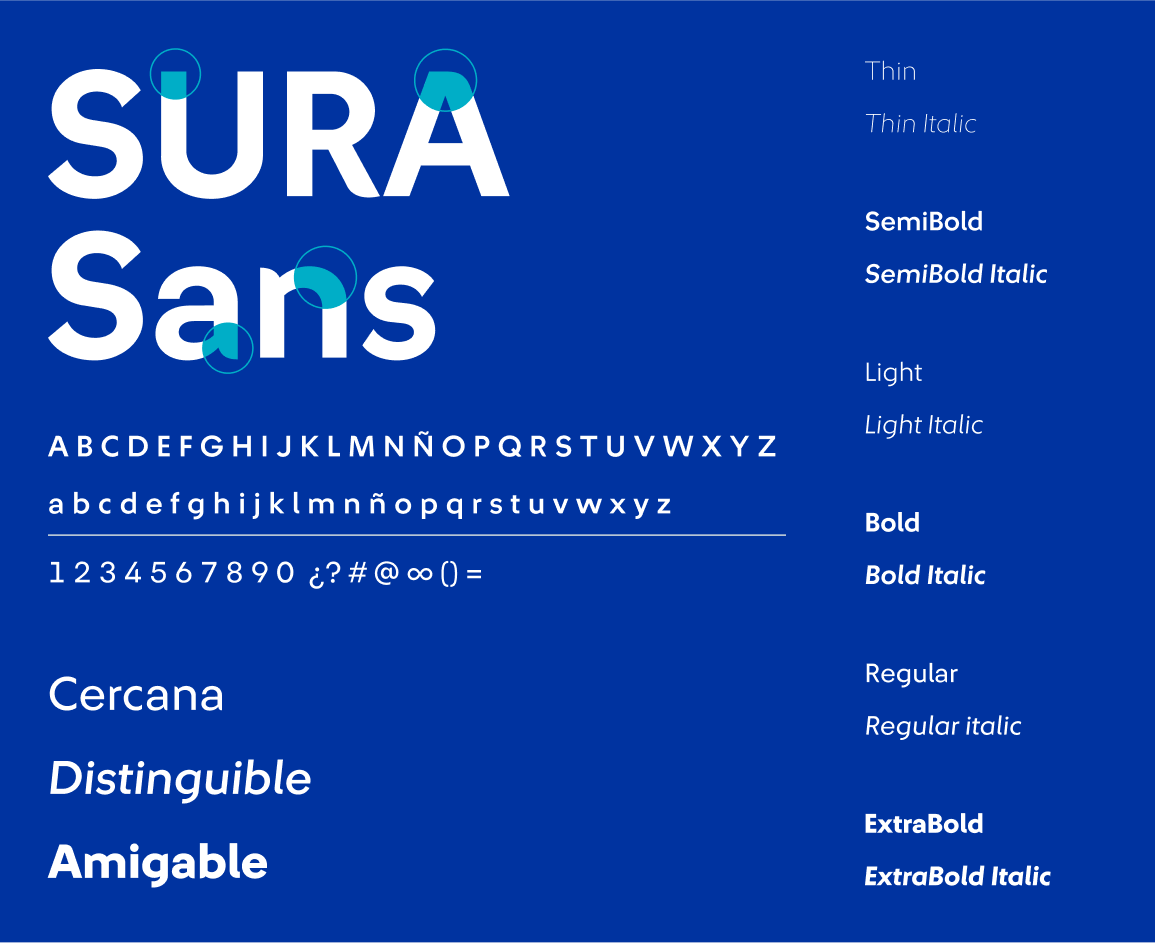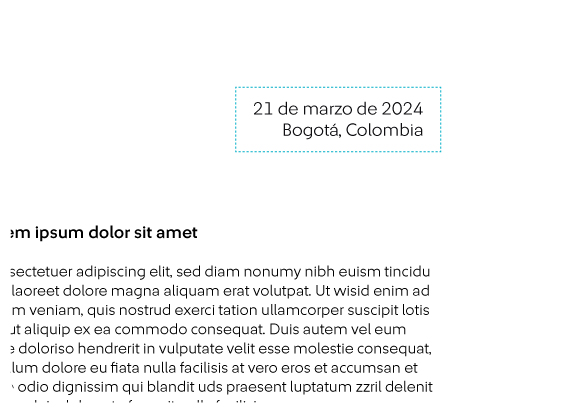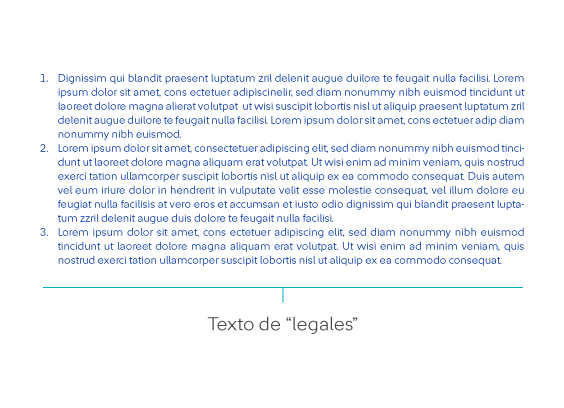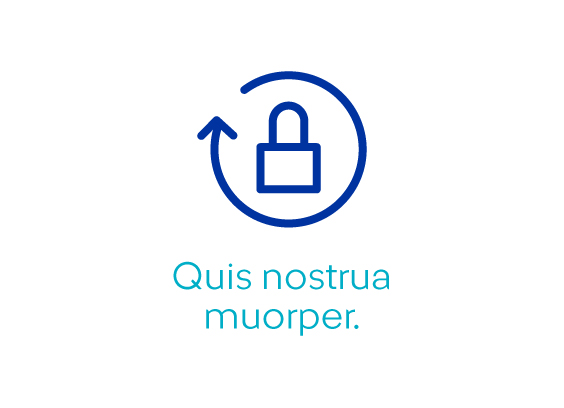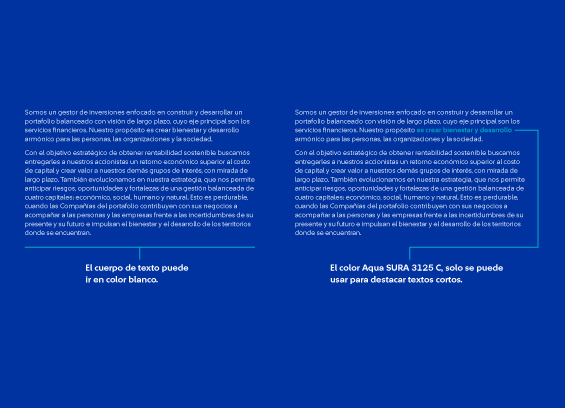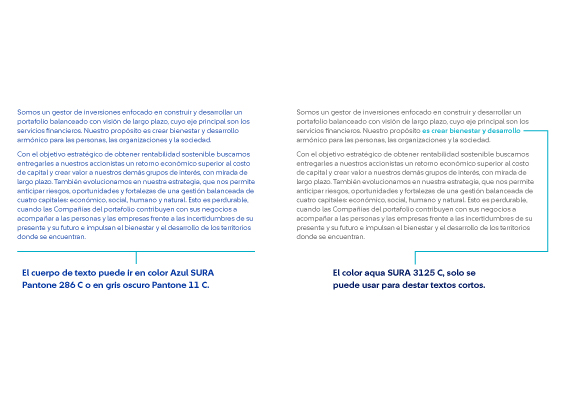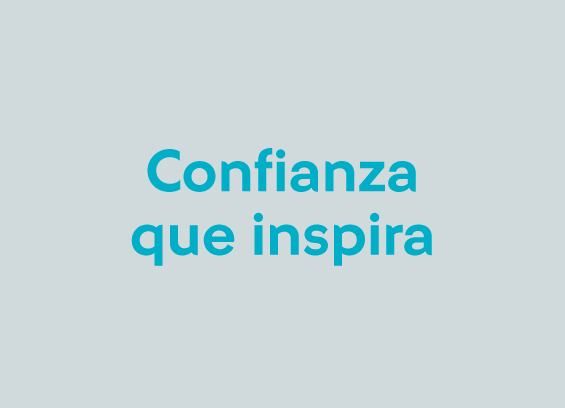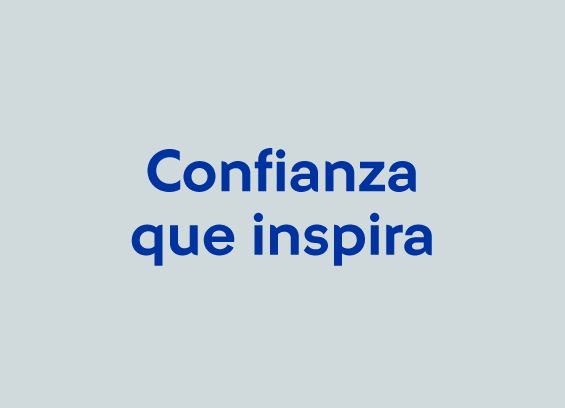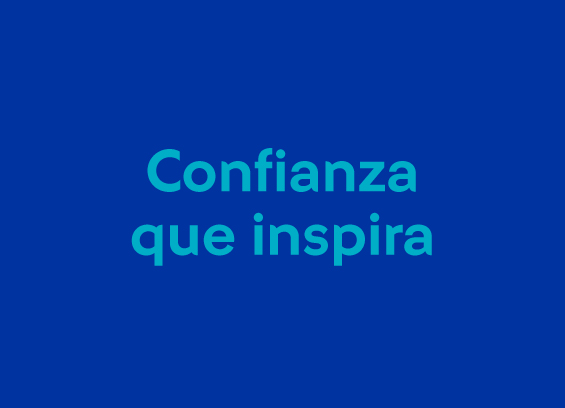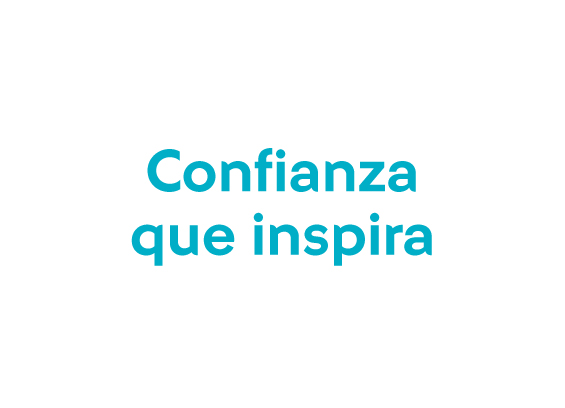
Tipografía
SURA Sans fue diseñada exclusivamente para la marca, cuenta con una personalidad única que refleja los valores de la marca.
Jerarquía tipográfica
Para enfatizar la relevancia de las diferentes secciones de un mensaje se debe hacer evidente la jerarquía que posee cada sección.
Ejemplos
Se puede hacer evidente la jerarquía mediante el contraste de 3 elementos: peso, color y uso de mayúsculas.
Justificación de textos
Alineación a la izquierda
Los textos deben ser alineados principalmente al lado izquierdo. Solo por motivos necesarios, se pueden usar otros tipos de alineación.
Casos especiales
Solo por motivos específicos dónde se acredite la necesidad de usar otro tipo de alineación de texto que no sea a la izquierda, se puede usar otro tipo de alineación de texto. Algunos ejemplos de ello son:
- Alineación al centro: a) Titulares con muy pocas palabras, b) textos cortos que se ubiquen en la parte inferior de íconos.
- Alineación en bloque: en cuerpos de texto de información legal. Para este tipo de alineación es necesario cuidar el corte de palabras.
- Alineación a la derecha: a) fechas de documentos – cartas, b) citas – notas.
Kerning y Tracking
El espacio entre letras (tracking) y entre líneas de texto (kerning) debe ser balanceado para crear una lectura cómoda y fluida.
Al tener un kerning y tracking, muy abierto o muy cerrado, se generan textos incómodos y difíciles de leer.
Tipografía y color
Cuerpos de texto
Cuando el fondo es de color Azul Profundo los cuerpos de texto deben de ir en blanco.
Si el fondo es de color blanco los cuerpos de texto pueden ir en color Azul Profundo o en Gris Oscuro.
Titulares y textos destacados
Los siguientes ejemplos muestran las combinaciones aprobadas de color en titulares – textos destacados y color de fondo.